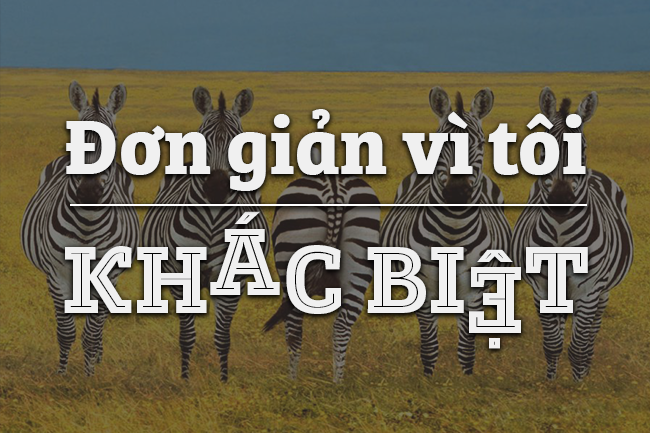
Posterizer KG Inline về cơ bản là phiên bản Inline của font Egyptian Slab Serif Posterizer KG. Posterizer KG Inline rất hữu ích cho bằng khen, tạp chí, tiêu đề và nhiều mục đích thiết kế khác.